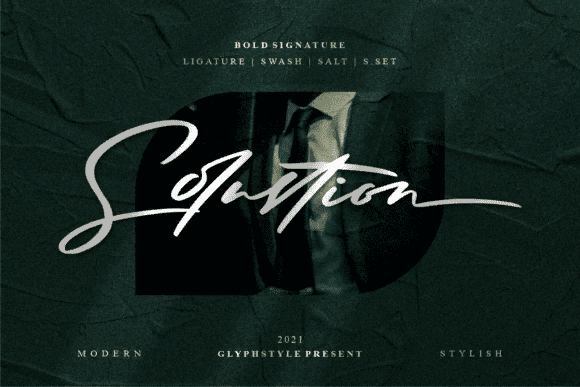
Название: Solustion Font (2021)
Solustion - это тонкий и модный шрифт, который излучает элегантность и класс.
Этот шрифт был создан специально для тех, кому нужен красивый и освежающий вид их дизайна.
Название: Solustion Font (2021)
Solustion - это тонкий и модный шрифт, который излучает элегантность и класс.
Этот шрифт был создан специально для тех, кому нужен красивый и освежающий вид их дизайна.